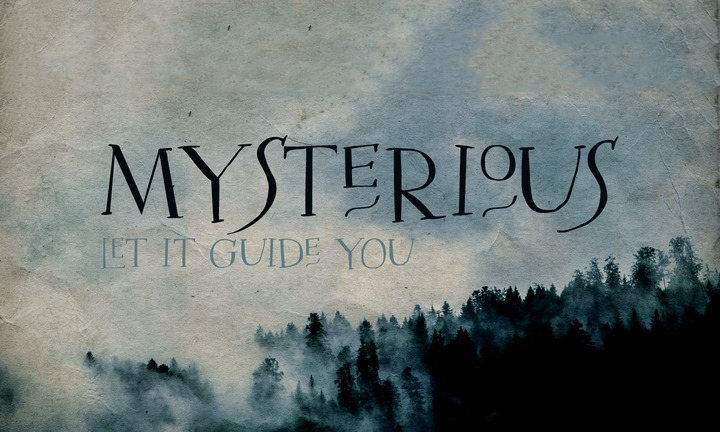
A Mysterious Typeface é uma nova adição à família de fontes serif da Hanoded. Inspirada no Tompouce Font, mas com um twist mais audacioso e antiquado. Ela se destaca por suas alternativas estilizadas que a fazem parecer antigamente desenhada, embora não seja exatamente um didone, mantendo sua essência moderna e inovadora. Apesar de seu aspecto formal e distante, a Mysterious Typeface traz uma aura perturbadora e assustadora que faz do seu uso um verdadeiro choque visual. Perfeita para designers buscando adicionar algo realmente único ao design de seus projetos gráficos, a Mysterious Typeface oferece tanto versatilidade quanto profundidade estilística. Ideal para criar um impacto no layout ou em qualquer aplicação que busque destacar-se.